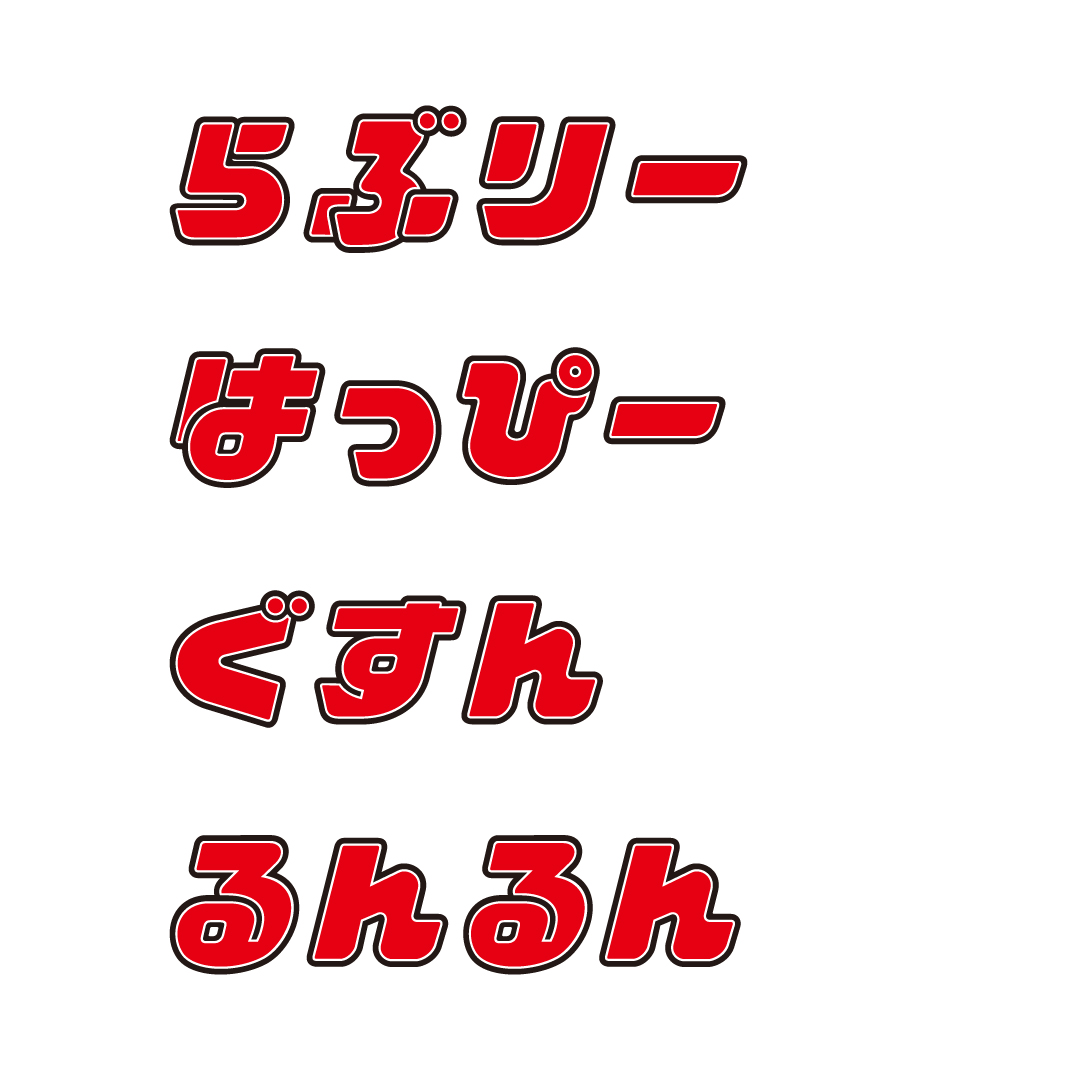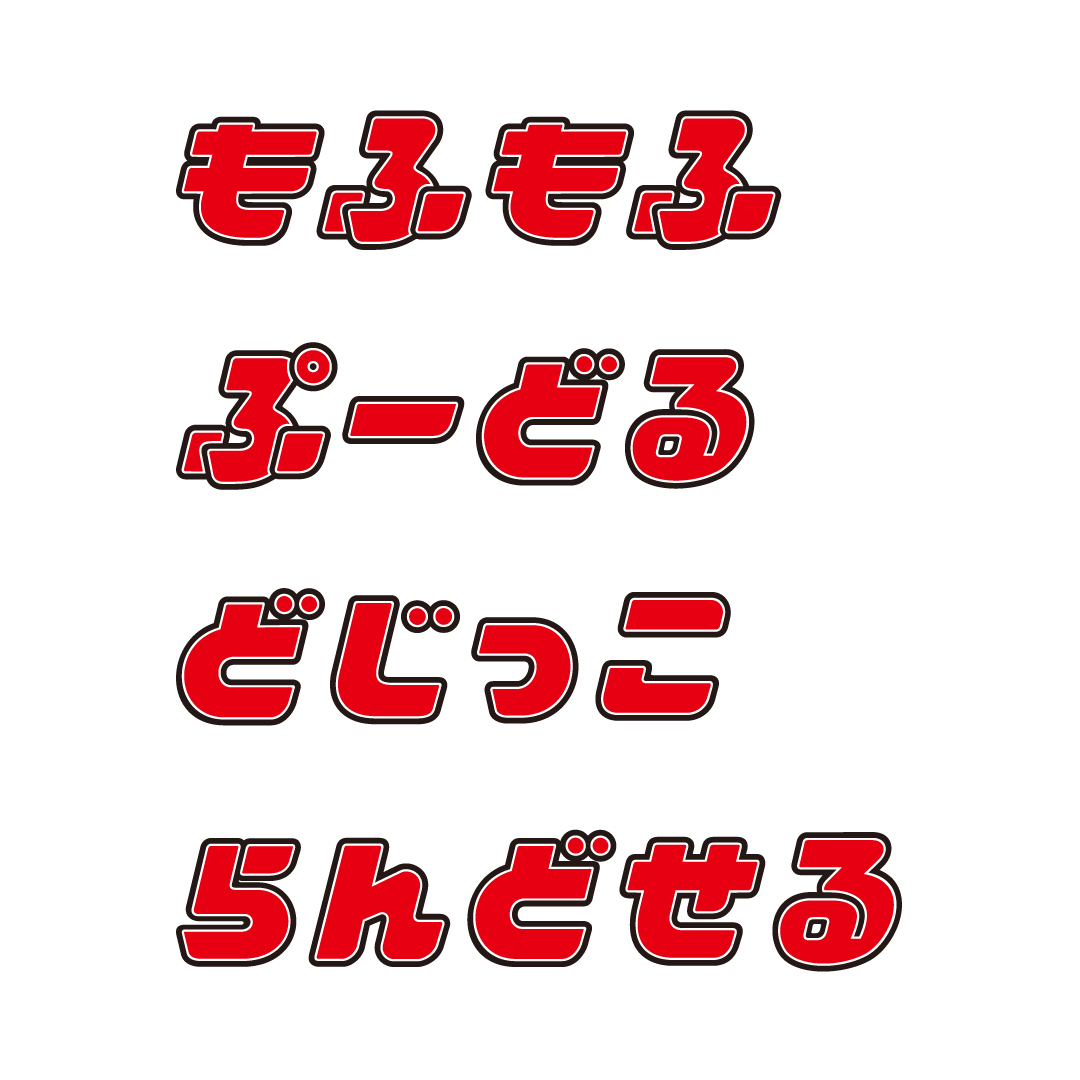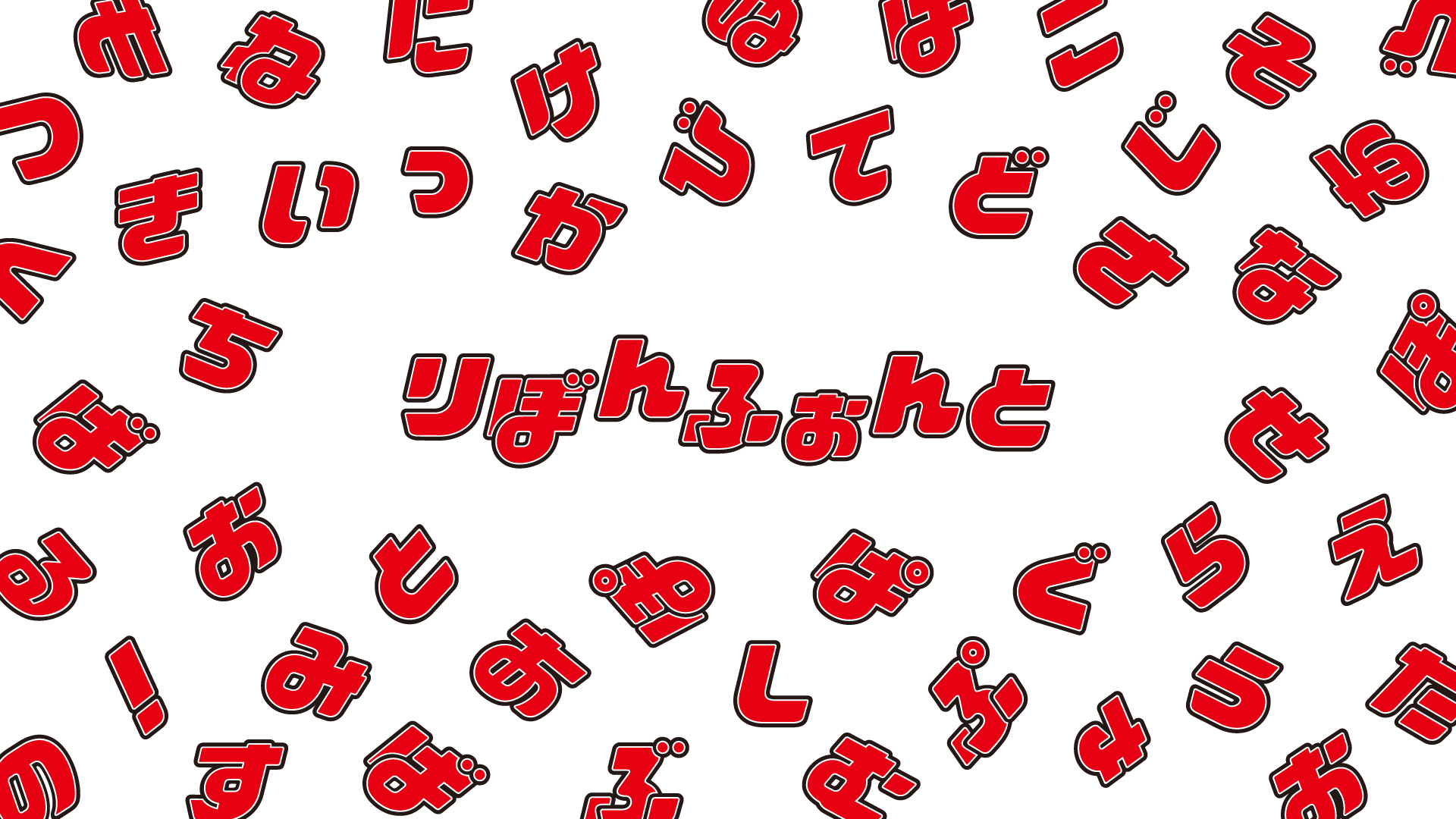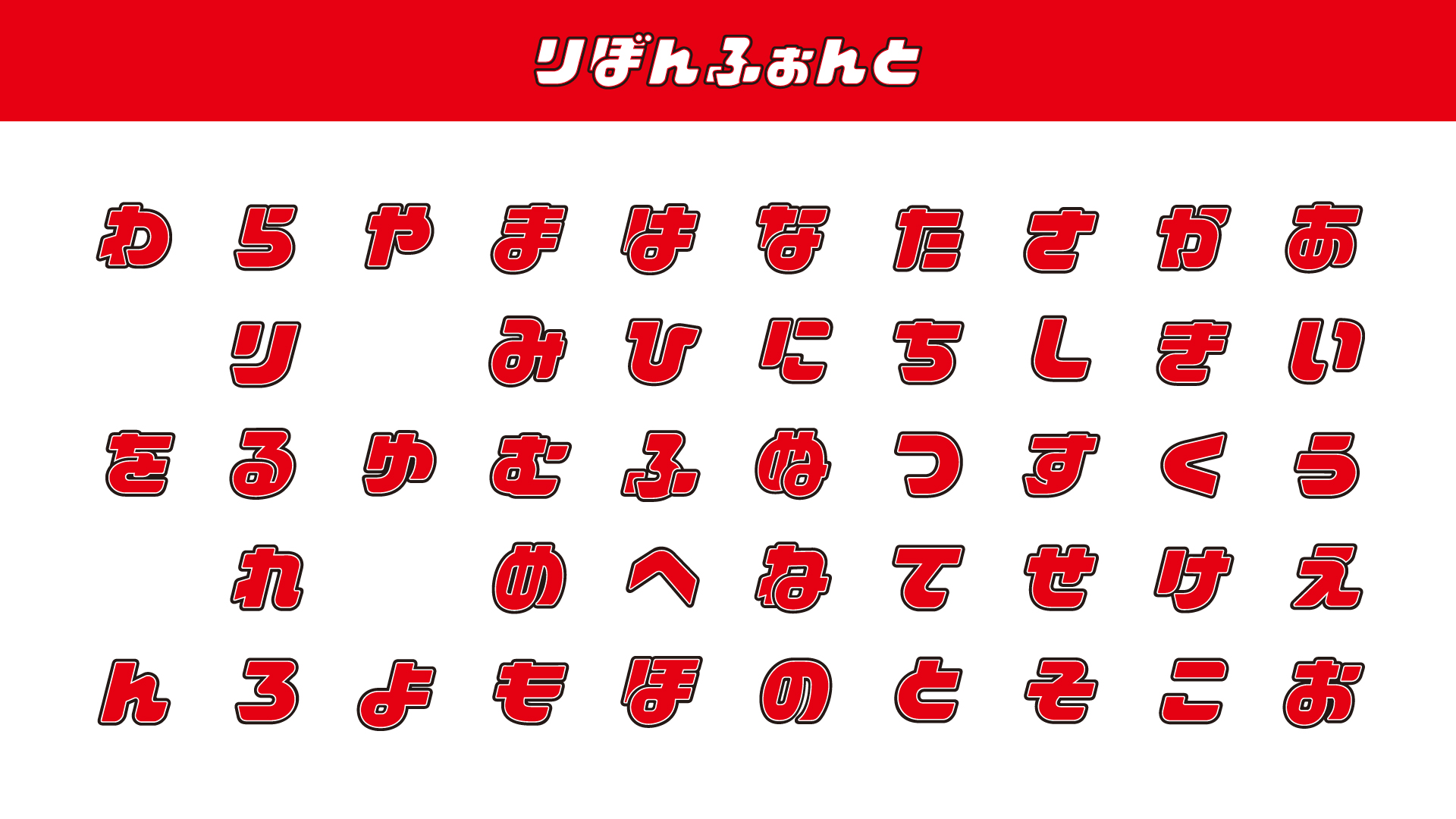
フォントワークス株式会社は、株式会社集英社が1955年より発行する少女まんが雑誌「りぼん」の創刊65周年を記念して始動する、「りぼん」創刊65周年プロジェクト【りぼんのりぼん】に参画し、「りぼんふぉんと」の制作を行いました。
「りぼんふぉんと」について
フォントワークスは、「り」「ぼ」「ん」の文字から、五十音のひらがなを作り出す取り組みに参画しました。まず、ロゴをもとに、文字のルールを構築。そして、濁音・半濁音も含めた書体へと展開し、95文字の書体を制作いたしました。
本取り組みでは、「のらもじ発見プロジェクト」などで知られるアートディレクターの下浜臨太郎さんと共に企画内容を詰め、完成に至りました。